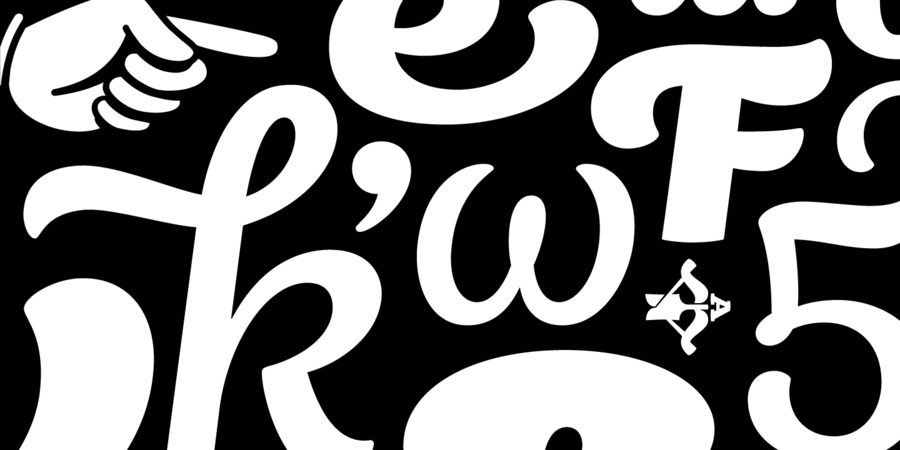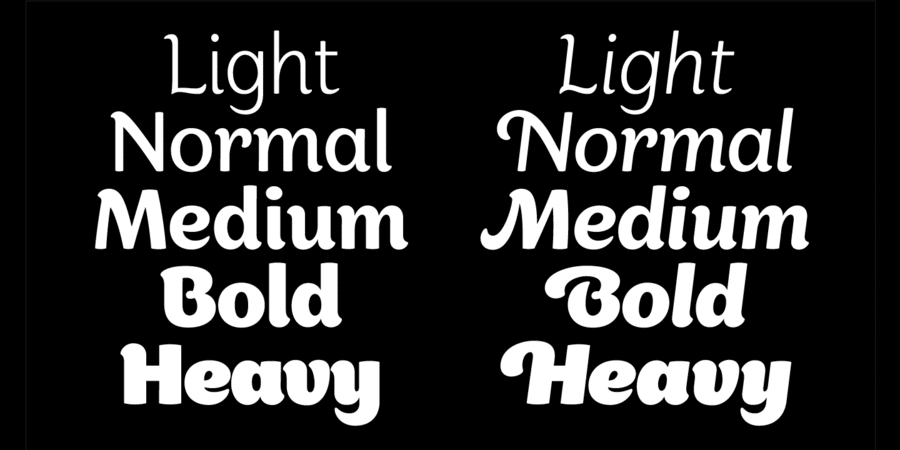
Appetite Pro – це повне оновлення популярного в усьому світі шрифту Appetite (2011). Шрифт заснований на оригінальній літерації в формі м'якого прямого крусива. Гарнітура Апетит Про складається з 10 накреслень з оновленим контуром. 5 прямих і 5 нахилених, від Світлого до Наджирного. Це багатомовне шрифтовое сімейство з підтримкою повної західної латинки, кирилиці й новогрецької абетки.
Апетит Про розроблений спеціально для харчової айдентики й дизайну упаковки. На додаток до стандартних наборів символів, шрифт включає неалфавітні знаки. 10 накреслень цього сімейства допоможуть вирішити безліч професійних дизайнерських завдань без витрачання грошей на додаткові шрифти для заголовків, підзаголовків та основного тексту.
Шрифт розробив Денис Серебряков у 2016 році.
Хіт 2010-х Схожий на шрифти з логотипів, ігор, фільмів:
Lays, Fake News, Фрекен Бок
плакат, журнал, листівка, привітання, анімація, мультфільм, лист, запрошення, меню, етикетка, пакування, реклама, афіша, стінгазета, відео, обкладинка, візитка, лендінг, щоденник, вивіска, стікер, наліпка Адаптованість гарнітури до носіїв:
Асоціації з сімейством шрифтів Appetite ProОсобистість і характер гарнітури:
легкий, хіпстерський, добрий, наївний, милий, М'який, чесний, рукотворний, екологічний, доброзичливий, довірчий, зелений, натуральний, природний, теплий, ламповий, здоровий, гнучкий, модний, грайливий, потішний, гладенький, прикольний, привітний, красивий, свіжий, характерний, акуратний, мотузковий, круглий, бадьорий, святковий, домашній, літній, симпатичний, няшний, худий, приємний, чистий, ніжний, делікатний, рівний, якісний, культурний, добірний, дорогий, елегантний, майстерний, естетичний, витончений, художній, знаменитий, оригінальний, сучасний, пластичний, жіночний, романтичний, затишний, комфортний, зрозумілий, ввічливий, ясний, спокійний, рослинний, мирний, зручний, динамічний, лихий, рухливий, радісний, смачний, апетитний, соковитий, стиглий, ефектний, яскравий, виразний, гармонійний, елітний, багатий, фруктовий, ягідний, сімейний, веселий, пузатий, добродушний, важкий, помітний, дитячий, мультяшний, щедрий, пишний, живий, товстий, усміхнений, солодкий, щасливий, зимовий, впевнений, урочистий, щільний, рідкий, новорічний, рясний, насичений, пухкий
кафе, їжа, відпочинок, природа, море, пляж, розваги, свято, табір, школа, дитяча книжка, квіти, щоденник, зошит, прикраса, селфі, дієта, сніданок, АСМР, чистота, гігієна, смузі, Хюґе, дизайн, ресторан, лосьйон, краса, туалетна вода, шампунь, Інстаграм, графіка, ілюстрація, дім, ранок, світанок, йога, велнес, торгівля, продукти, ремесло, ярмарок, фаст фуд, закуска, крамниця, одяг, взуття, піцца, десерт, подарунки, кондитерська, булочна, сік, торт, варення, шоу, телебачення, здоров'я, преміум, готель, шоколад, цукерки, вода, фрукти, мармелад, шаурма, соус, кетчуп, жуйка, підгузок, морозиво, кава, чай, фарба, виставка, фломастери, літо, родина, магазин, молоко, мафін, солодощі, випічка, кондитер, сметана, мед, масло, чіпси, сир, булочка, м'яка іграшка, фарби, анімація, іграшка, дитяче харчування, зоопарк, клоун, розфарбування, гра, пончик, зоомагазин, тварини, цирк, мультфільм, дитсадок, дитячий ранок, канікули, крем, згущене молоко, день народження, обід, вечеря, Новий рік, котики, пластилін Гарнітура має ознаки стилів: